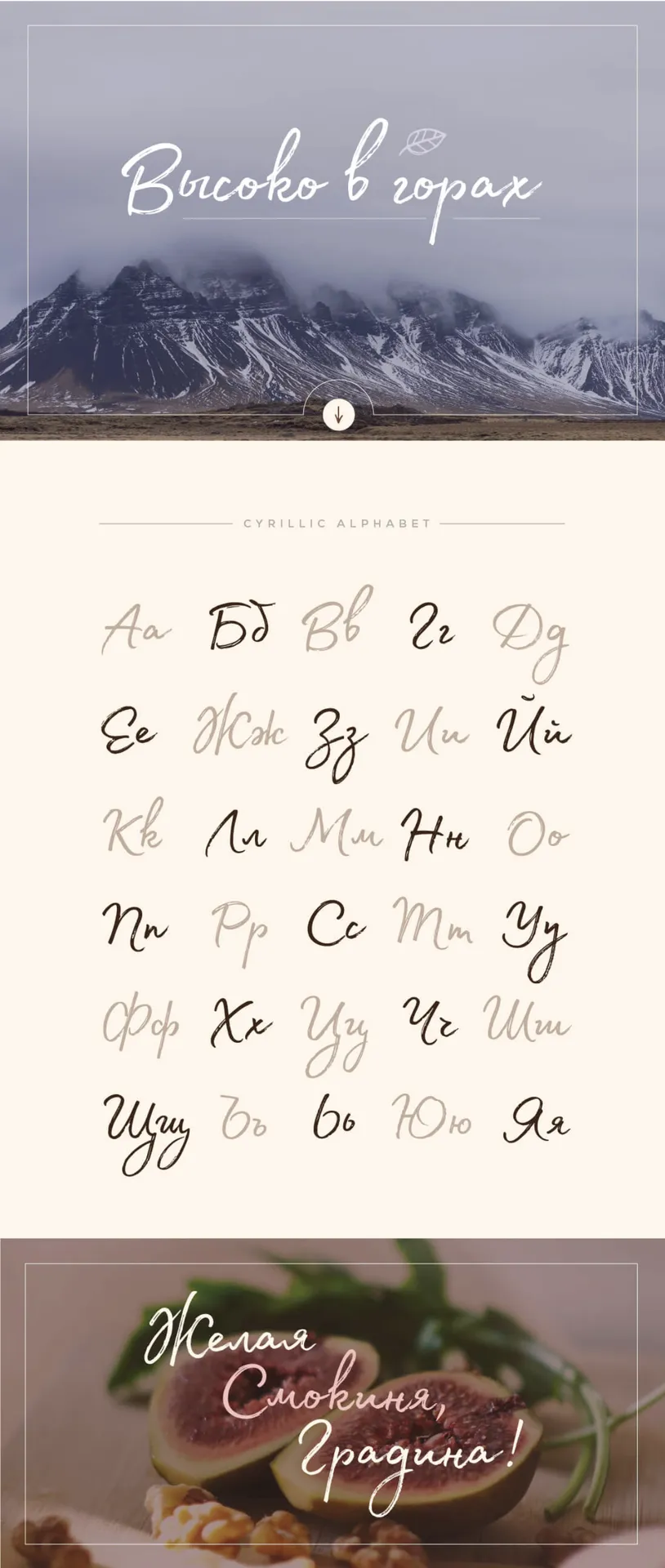
Красивый рукописный кириллический шрифт Madelyn Script Family
Beautiful Handwritten Madelyn Script Family — это профессиональный набор шрифтов, выполненный в стиле рукописного письма. Данный пакет представляет собой коллекцию гарнитур, предназначенных для использования в графическом дизайне, оформлении полиграфической продукции, создании логотипов, брендинге и веб-дизайне. Продукт ориентирован на пользователей, которым требуется придать своим проектам эстетичный, элегантный и индивидуальный рукописный вид.
• Набор включает в себя семейство шрифтов Madelyn Script, отличающихся уникальной стилистикой рукописного начертания.
• Высокая детализация символов позволяет использовать гарнитуры в проектах с высоким разрешением без потери качества.
• Гибкость применения: подходит как для заголовков и акцентных надписей, так и для декоративного оформления элементов интерфейса.